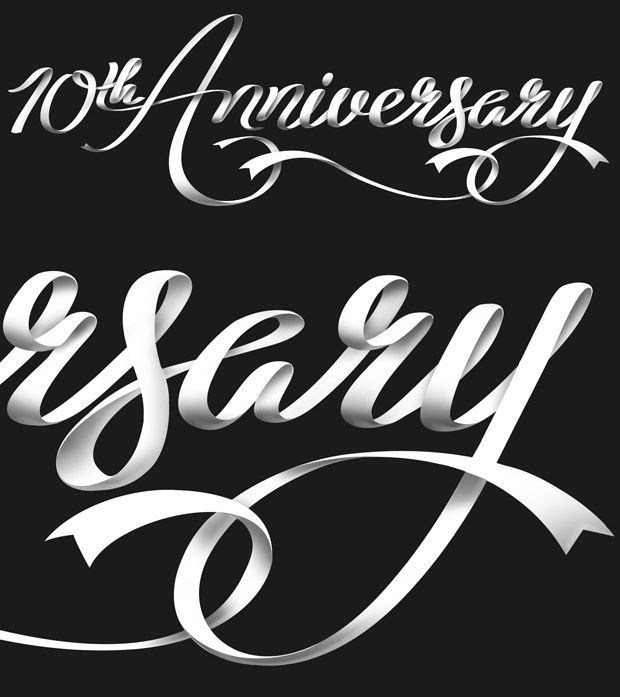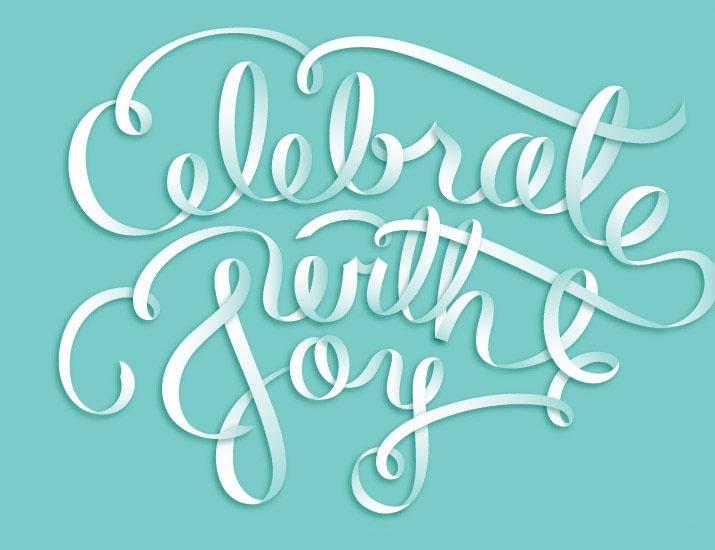
20 красивых ленточных шрифтов для элегантного и женственного дизайна
Сегодня мы выбрали для вас действительно привлекательных ленточных шрифтов . Это не просто обычные ленточные шрифты. В некоторые из них добавлены действительно спецэффекты. У этих шрифтов действительно красивые изгибы, и вы можете использовать их для различных проектов. Некоторые из этих ленточных шрифтов выглядят более женственными и элегантными, а другие более мужественными и современными. Проверь их!
Это очень классный дизайн шрифта из лент с градиентом, примененным к ним, для тонкого 3D-эффекта! Мне нравится, как буквы растушевываются на стыках.
Tribbon — это вкусный многослойный шрифт в стиле «ленты», как говорит noupe.com. Он был создан Домиником Ле-Хейром и представляет собой рабочий шрифт в стиле «ленты», состоящий из нескольких слоев и совершенно бесплатный. Tribbon доступен в форматах шрифтов TTF и OTF.
Если вам нужно больше ленточных шрифтов, вот еще один классный. Лента теперь представляет собой полноэкранное изображение, включая функции Opentype для альтернативного алфавита. Он имеет прекрасный дизайн с винтажным оттенком, который сделает ваши дизайнерские проекты великолепными. Шрифт
Riesling можно загрузить бесплатно и использовать в своих проектах по своему усмотрению. Элегантный винтажный дизайн, который мне очень нравится. Надпись приятная и использует преувеличенные засечки, идеально подходящие для элегантных дизайнов.
Этот шрифт вдохновлен галисийскими народными шрифтами.
Он основан на древних каменных надписях, что делает его еще круче. Этот пример имеет два разных веса и может использоваться для разных типов проектов с разными темами.
Этот шрифт идеально подходит для детских открыток, специальных канцелярских принадлежностей или даже для причудливого заголовка блога. Этот пример доступен для загрузки только в виде изображения с высоким разрешением или векторного файла. Используйте этот ленточный шрифт для женских дизайн-проектов.
Этот шрифт обязательно должен быть в вашей коллекции. Кириллическая лента – это классный бесплатный шрифт с изящными и тонкими деталями. Это рукописный шрифт, который будет отлично смотреться в ваших проектах. Это просто и эффективно воздействует на зрителей.
Это еще один классный ленточный шрифт, который вы захотите скачать немедленно. Этот пример имеет детский дизайн, и его можно интегрировать во все виды творческих проектов, будь то печать или веб.
Этот ленточный шрифт предназначен для девочек и подходит для детей, а в его надписях есть солнечные точки.
Было бы очень интересно использовать его в макетах Disney. Вы можете сделать его еще круче, изменив цвета букв.